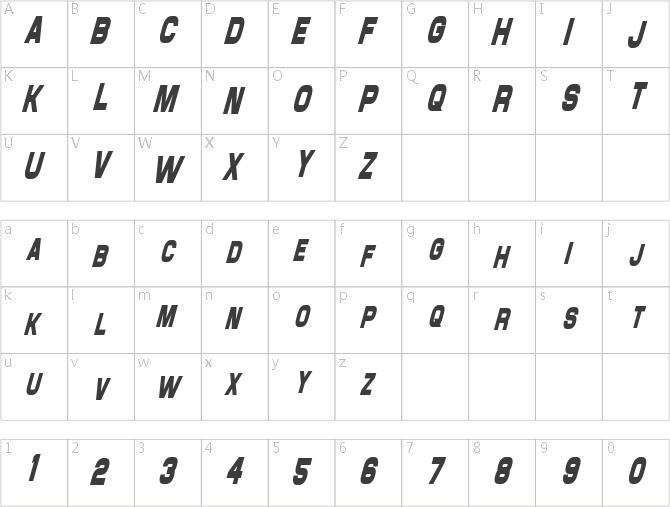
字体名称: Maximus
Maximus Condensed Bold Italic
Maximus Condensed Bold Italic介绍
Maximus Condensed Bold Italic字体字库是一款让人赏心悦目、百看不厌的英文字体,适合各类广告和产品包装设计应用,字体大小0.02MB,格式为ttf字体,上传用户是23KUN,作者/版权方为未知